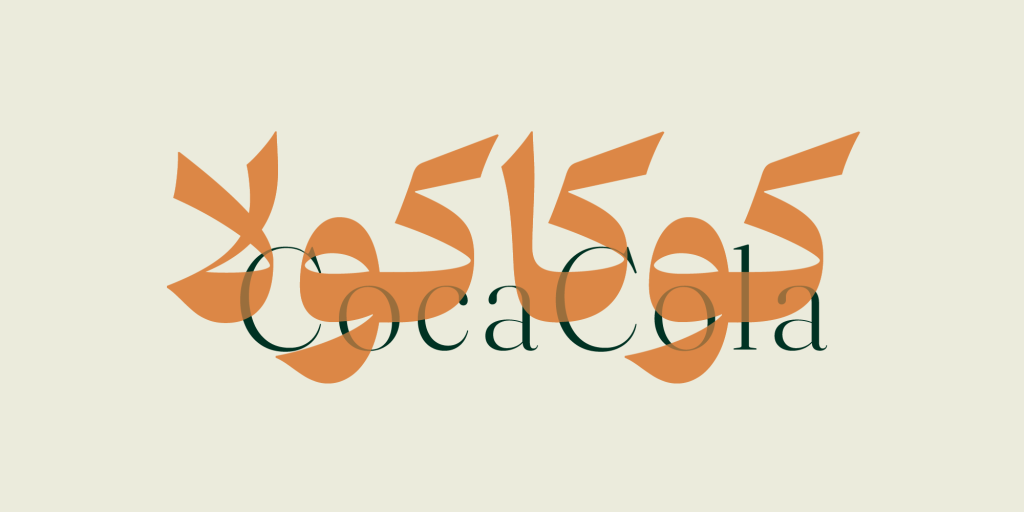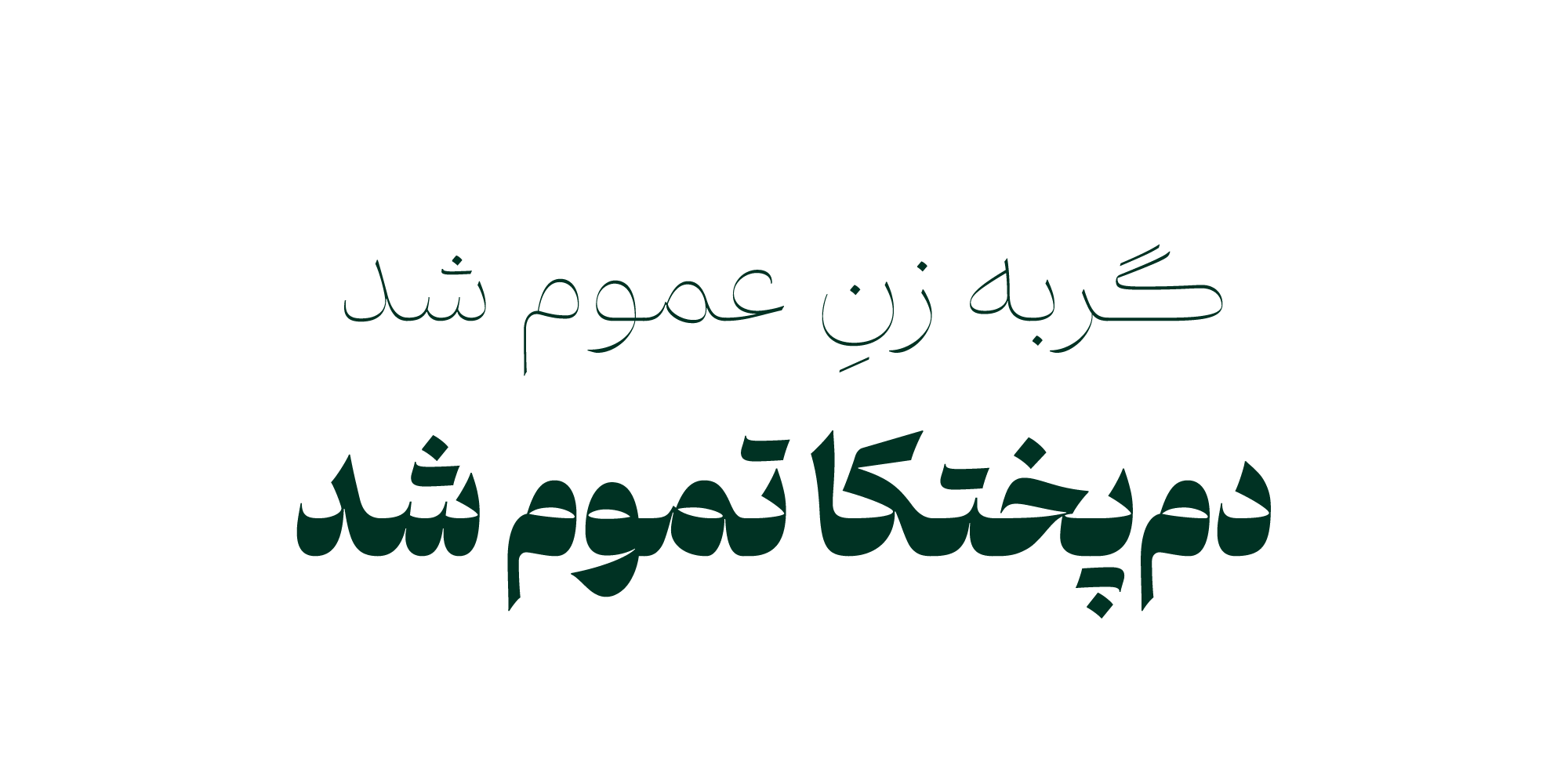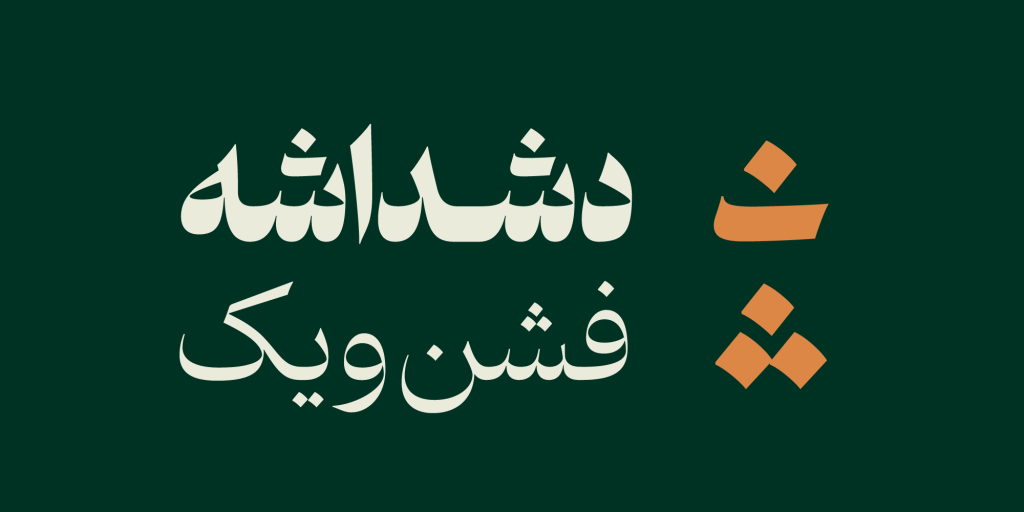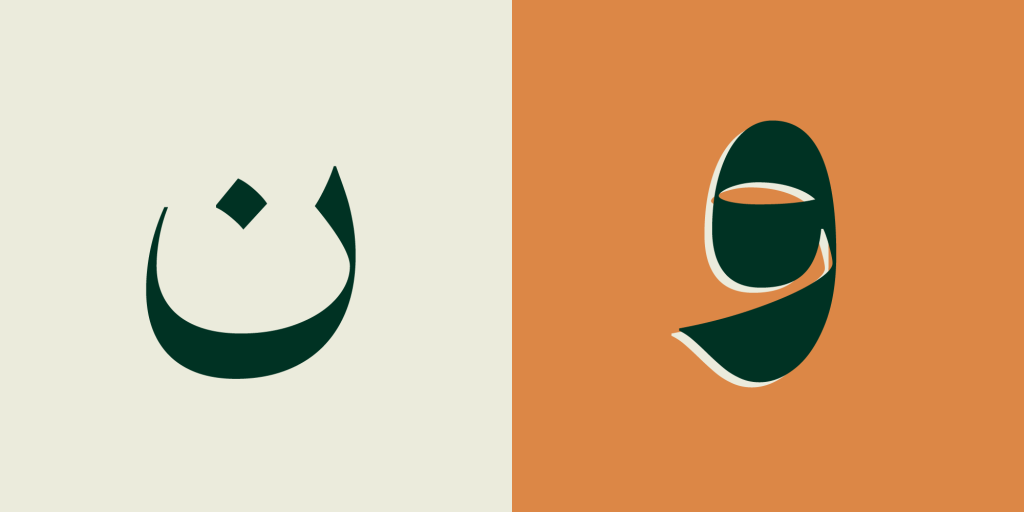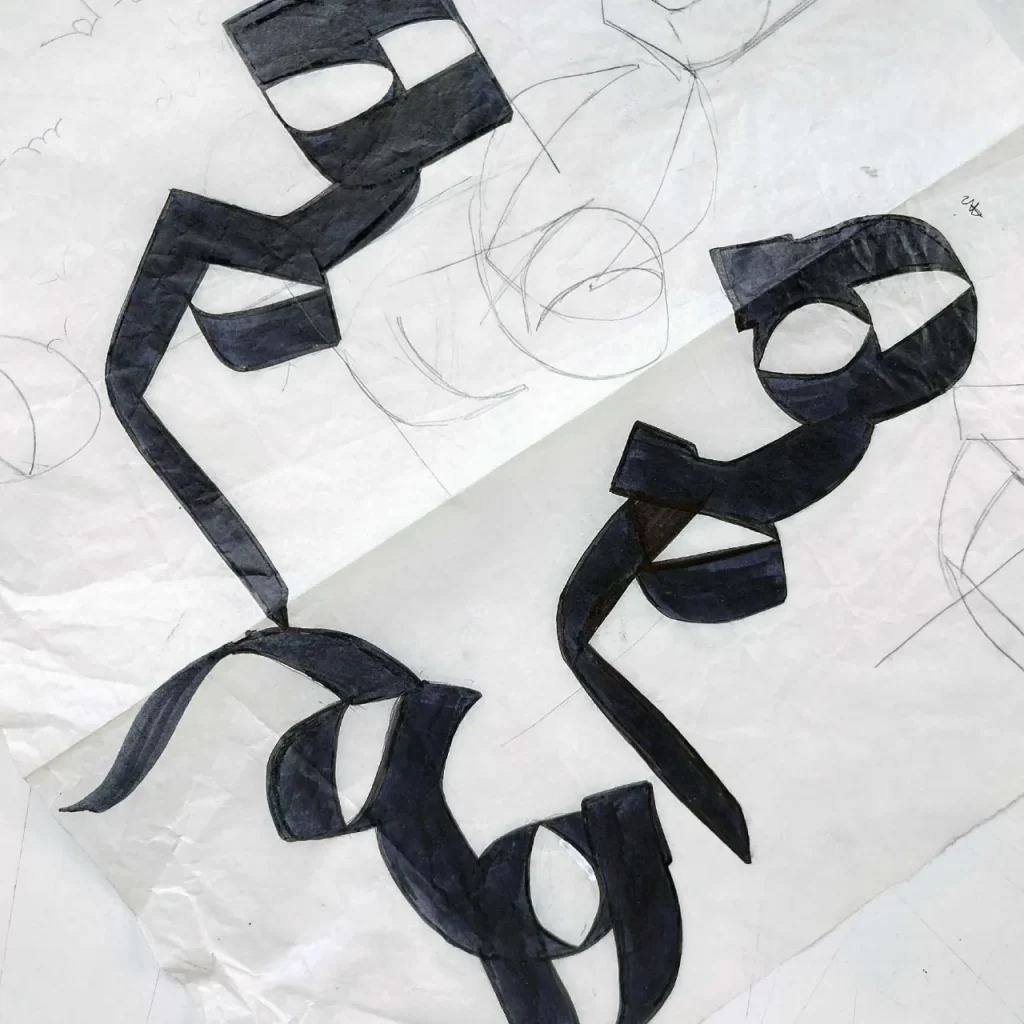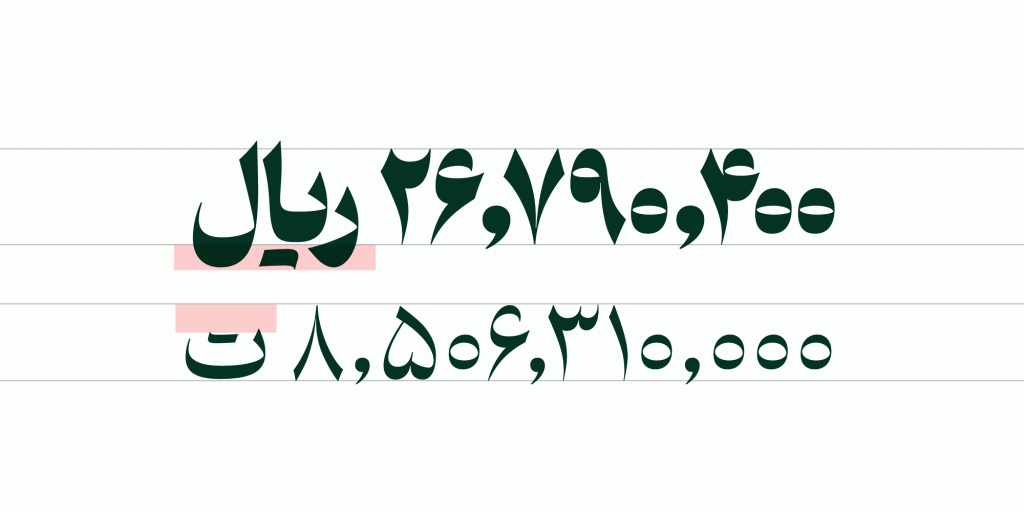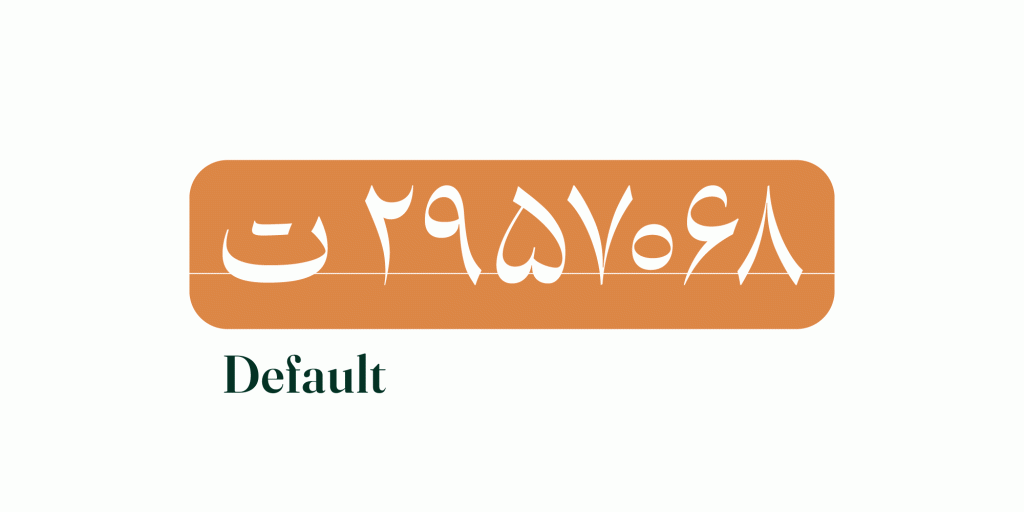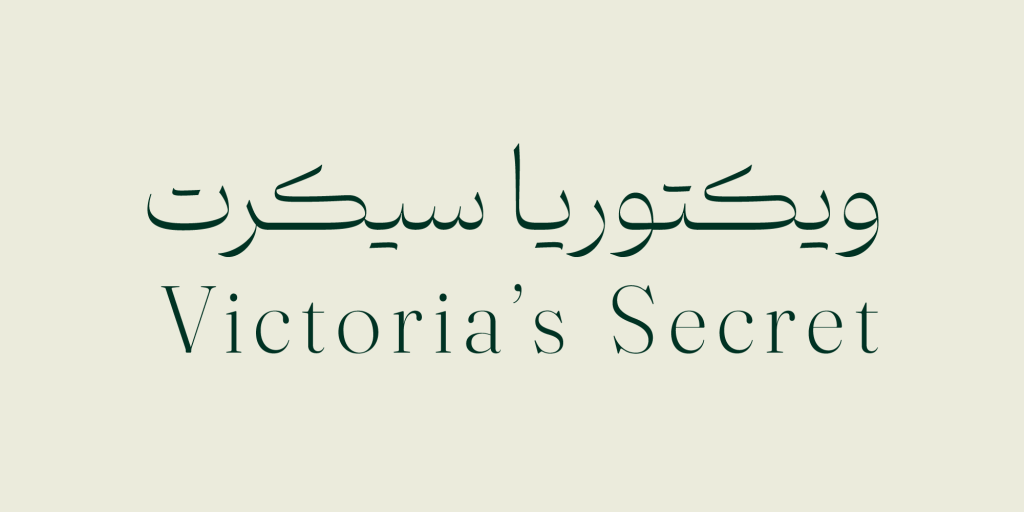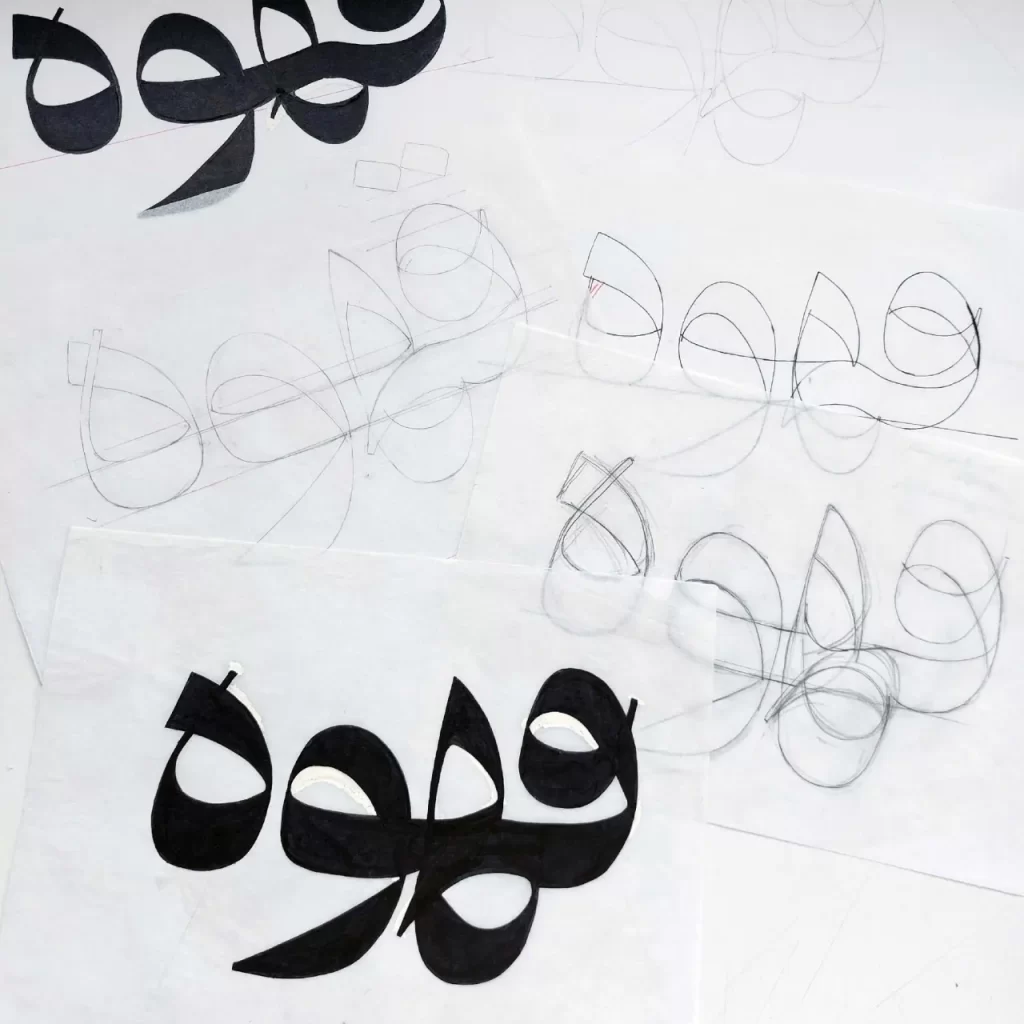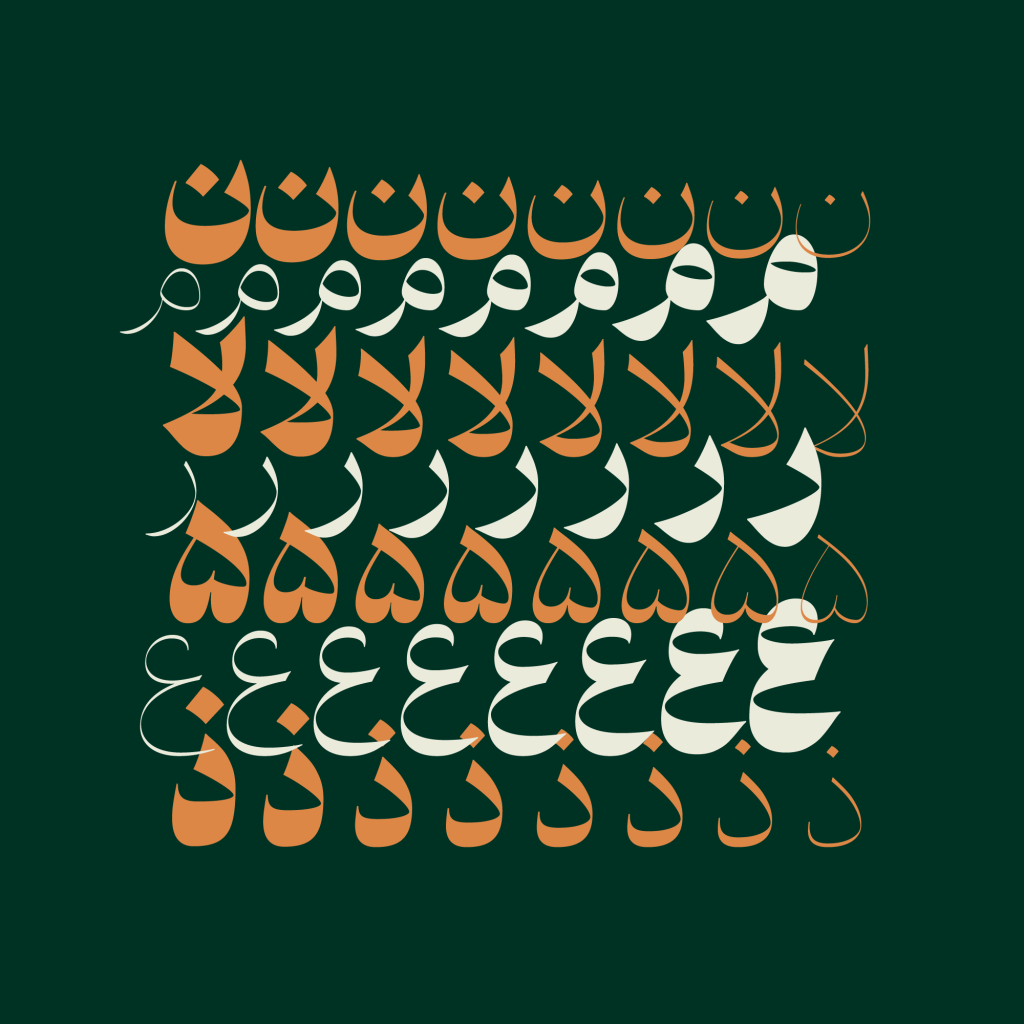
فونت دوران قلمی با قابلیت های فراوان
فونت دوران قلم و تایپ فیسی که هرچه لازم باشد در دل خود دارد. فرم های طراحی این تایپ فیس به گونه ای است که از منحنی های زیاد تشکیل گردیده و به ندرت خطوط صاف و مستقیم در آن یافت می شود مفصلها غالبا نرم و بدون شکستگیاند اما کنج ها و لبهها برنده و تیز می باشند. دوران با پشتیبانی از 8 وزن مختلف از نازک تا خیلی ضخیم تقریبا تمامی نیاز های طراحان را مرتفع می سازد.
اساسا دوران فضا و اتمسفری کلاسیک دارد و در همنشینی با تایپ فیس های لاتین کلاسیک هماهنگی لازم را برای تاثیر گذاری خود انجام می دهد . کاربرد آن در فضا های رسمی و کلاسیک و تاریخی و .. می باشد . می توان با استفاده از نرم افزار های طراحی از جمله آدوبی ایلسترتور ، فتوشاپ و حتی اینشات برای طراحی پوستر ها ، جلد کتاب و مجلات ، پست های شبکه های اجتماعی و … اقدام نمود . حیطه کاربردی دوران از دنیای وب و دیجیتال تا صنعت چاپ و مطبوعات وسیع و گسترده است.
پشتیبانی از زبان های مختلف در تایپ فیس دوران
فرشته ایرانشاهی و رضا بختیاری فرد با همکاری یکدیگر دوران را در بازه زمانی 5 ساله طراحی نموده اند. همین زمان موید دقت و توجه به جزئیات و ظرافت های زیبایی در طراحی این قلم است. در این قلم حروف زبان های مختلف به جز فارسی نیز طراحی گشته است تا دوران از زبان های دیگری از جمله انگلیسی , اُردو , عربی , کوردی هم پشتیبانی نماید.
ترکیبات و حروف جایگزین فونت دوران
فونت دوران با پشتیبانی از حروف و ترکیبات جایگزین زیبایی و خلق تنوع بیشتر را برای شما به ارمغان می آورد. در فایل راهنمای این تایپ فیس تمامی توضیحات لازم در خصوص استفاده از این ترکیبات جایگزین ارائه گردیده است . در زیر تصاویری نمونه از این قلم برای شما مهیا شده است.
این قلم از زبانهای فارسی، عربی، کردی، اردو و انگلیسی پشتیبانی میکند.